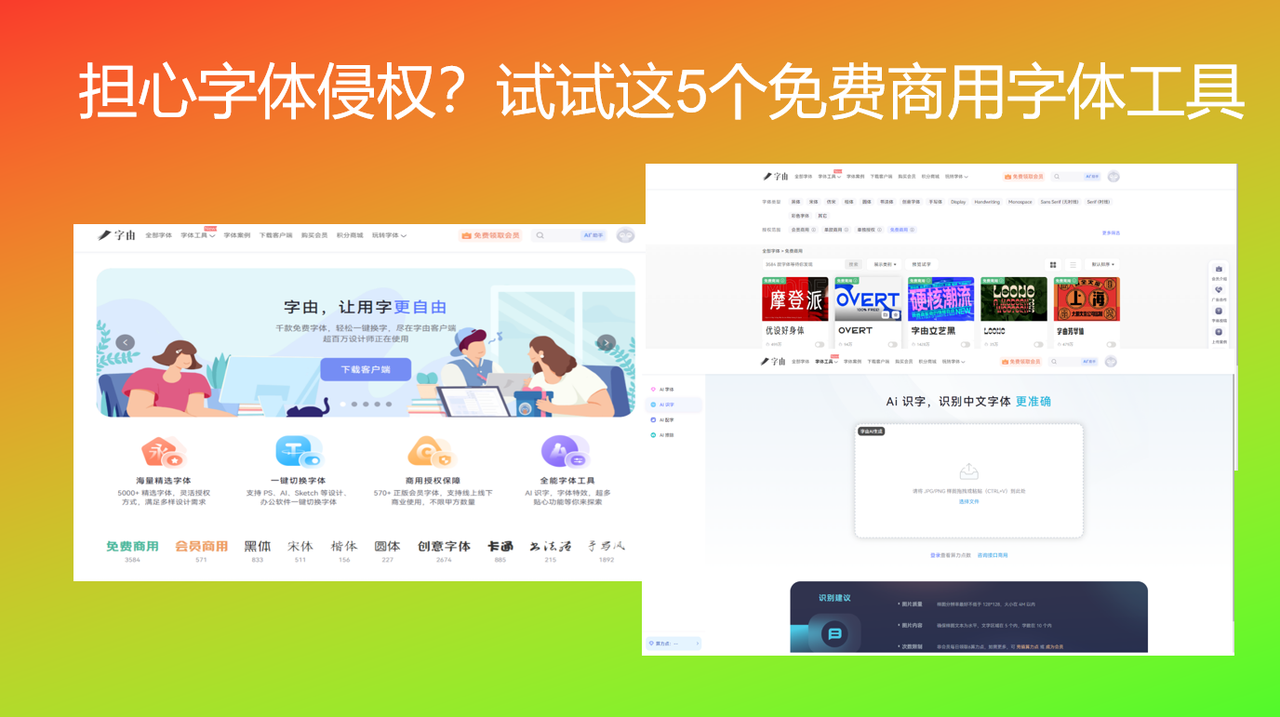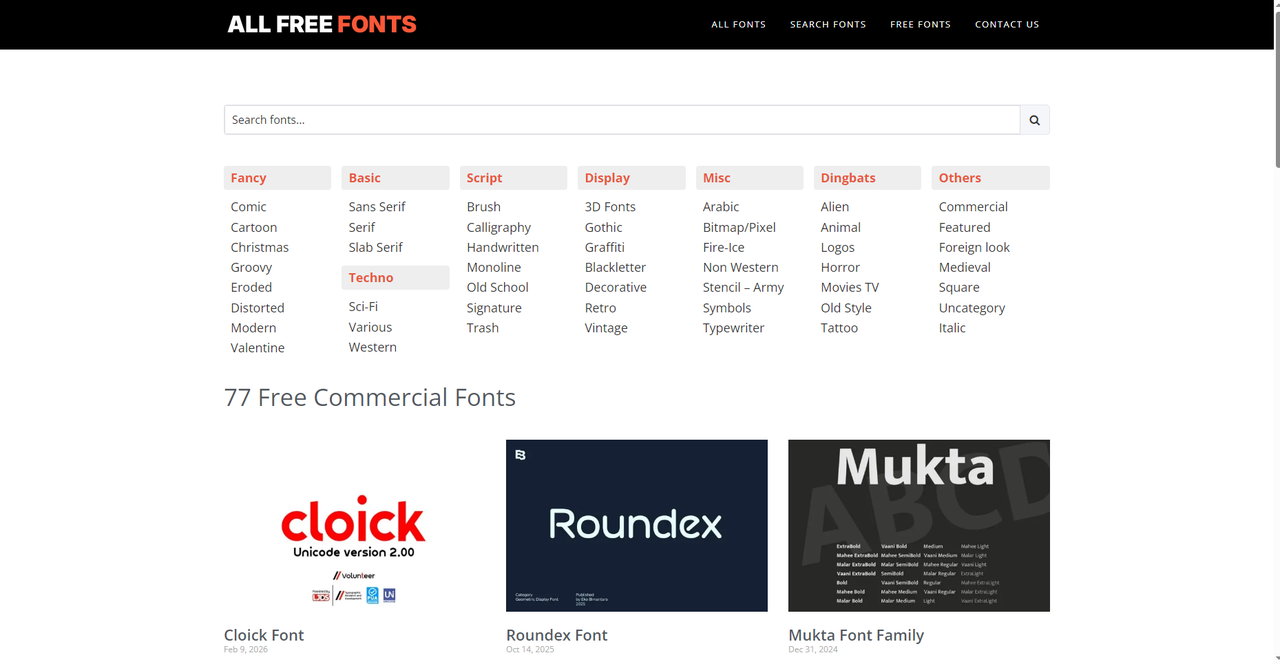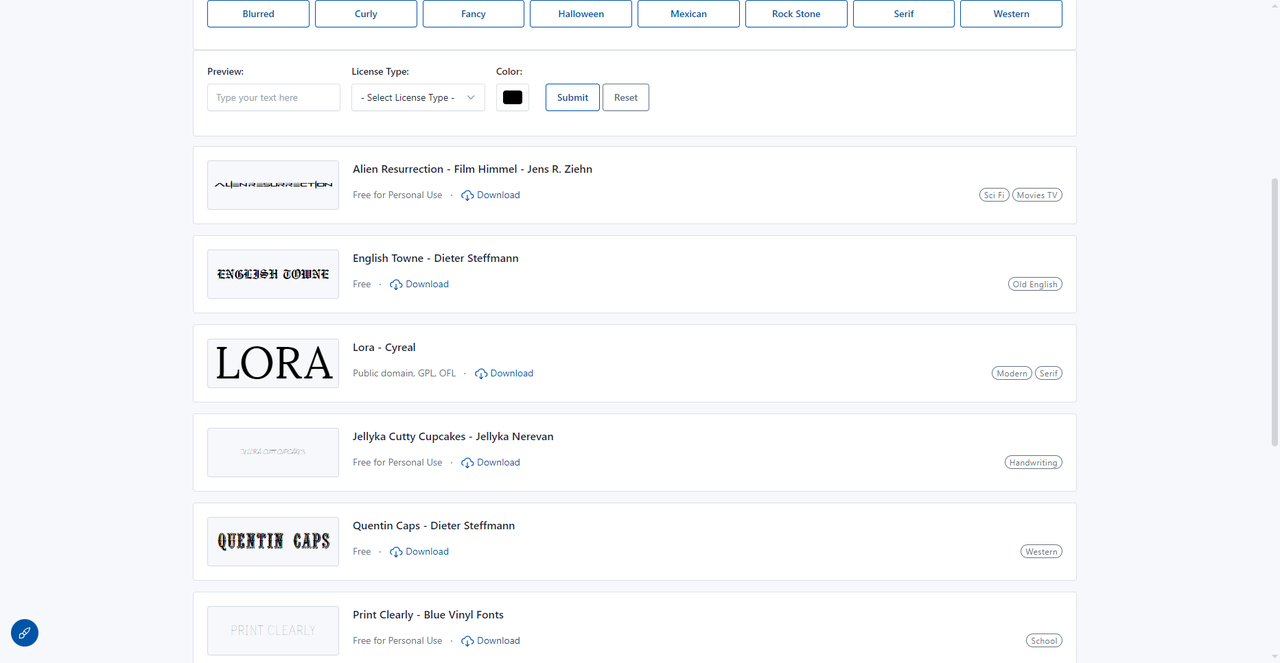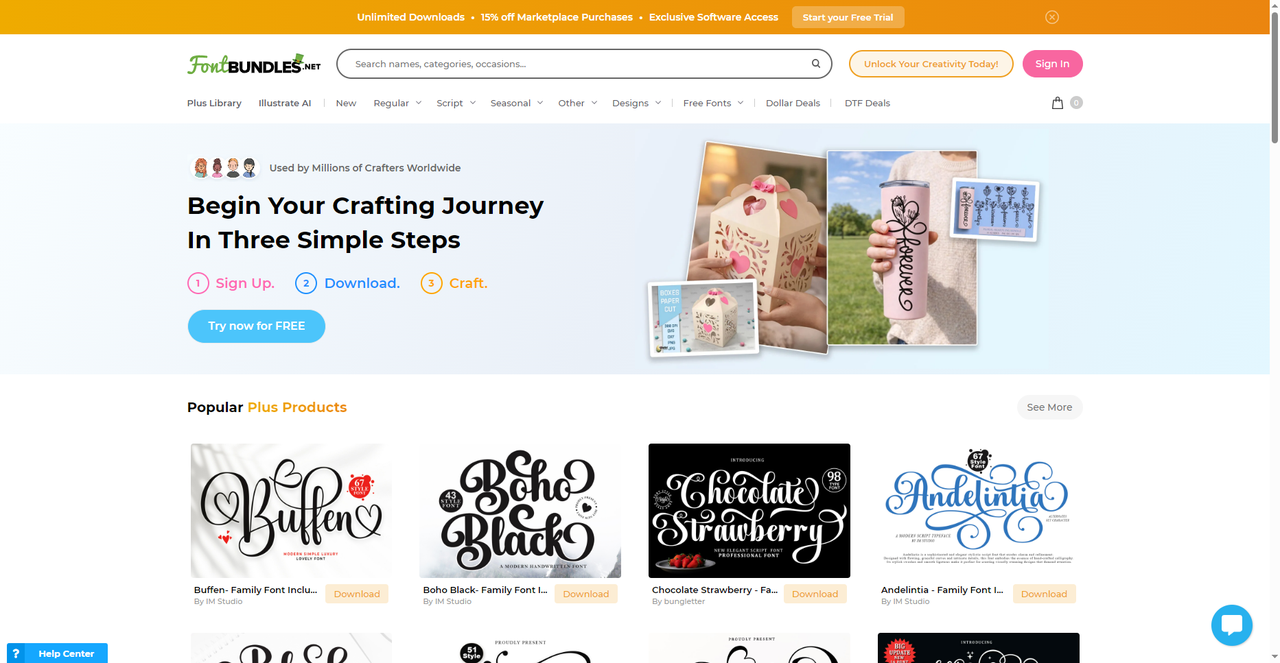
担心字体侵权?试试这5个免费商用字体工具
做设计的最怕什么?不是没灵感,也不是要面对甲方的反复改稿,而是辛辛苦苦做完了作品以后才被人告知作品里的字体并不是免费使用,是有版权的。网上搜来的字体还要查半天有没有是授权,就算有授权了还不一定能够商用,一般情况就是好不容易找到一款合适的,下载下来才发现“仅限个人使用”。但是总的来说,字体侵权这件事只需要找对字体平台就可以避免,也就是用好免费商用字体生成工具。今天我就筛选了 5 个亲测可用的免费商用字体生成工具,从国产神器字由到国外精选平台,每个都标明了字体数量和授权方式,再也不用担心授权问题了!
第一个要推荐的免费商用字体生成工具是字由,目前来看,字由收录了超过10500款字体,其中3584款是免费可商用的,这个体量意味着什么?就是你日常设计需要用到的字体,基本都能在这里找到,而且完全不用担心版权问题。接下来我会详细解释。
我也会给大家介绍几款我一直在用的免费可商用的字体:
• 字由文艺黑:既有黑体的稳重又带手写感,适合标题、海报
• 优设标题黑:方正有力,适合电商设计、活动海报
• 江西拙楷:手写楷书风格,适合国风、文创设计
• 字由芳华体:手写风格,笔画柔和,适合文艺类设计
• 思源黑体 Medium:经典开源字体,适合正文排版
2、ALL FREE FONTS
这个网站里有大量的字体,但是只有77 款免费商用字体,如果在其他地方找不到合适的字体也可以来这里看看,这个网站提供了非常详细的分类标签:
我的话会推荐cloick、Roundex 和 Mukta Font Family 等字体,适合多场景使用。每款字体都标注了上传时间,方便你判断新旧程度和适用范围。如果你需要大量筛选,这个网站的分类逻辑能帮你快速定位。
3、Free Fonts(1001 Free Fonts)
这个网站是知名的1001 Free Fonts,从2000年左右就开始运营,积累了上万款字体资源。首页有按字母A-Z排列的索引,也有按风格分类的大量标签,但如果你不想研究分类,直接看推荐区也能找到不少好东西。这个网站最大的优点是字体量大、风格全,几乎能找到任何你想要的款式。但正因为量大,筛选起来需要花点时间。建议先想好自己要什么风格,再用左侧分类定位,或者直接看热门推荐。下载前一定看清授权说明——有的免费商用,有的仅限个人,有的需要购买,千万别搞混。截图里同一页面上就有好几种授权类型,稍不注意就容易踩坑。
4、Craft Fonts
Craft Fonts 是一个极简风格的字体平台,和前面那些分类复杂的老牌网站完全不同。它的理念就是“简单”——从首页标语就能看出来:“Begin Your Crafting Journey In Three Simple Steps”(三步开启你的创作之旅):
这种简洁的流程对新手特别友好,不需要研究分类,不需要担心授权,注册下载就能用。底部还有“Popular Plus Products”热门推荐板块,方便你快速了解当下流行的字体风格,不用自己慢慢翻。这种“轻量化”的字体平台其实很符合现在的趋势。
5、Free Commercial Fonts
最后一个网站则是直接向我们展示了2款免费商用字体,和ALL FREE FONTS类似,也是走精选路线。但它的特点是每款字体都有详细说明和适用场景推荐,52款字体不算多,但每一款都是精挑细选的。
字体侵权这件事说到底还是信息差的问题,如果你能掌握好用的网站,那么字体侵权这件事就可以高效且轻松地被解决,如果手头上没有好用的网站,那或许你还会为字体版权这件事头疼。目前来讲我用着最是顺手的还是字由,因为它会直接在分类里给你指明哪些是有版权的需要付费的,哪些又是可以免费下载拿来商用的,这完全避免了侵权问题,选哪个不重要,重要的是以后做设计,不用再为字体版权提心吊胆了。